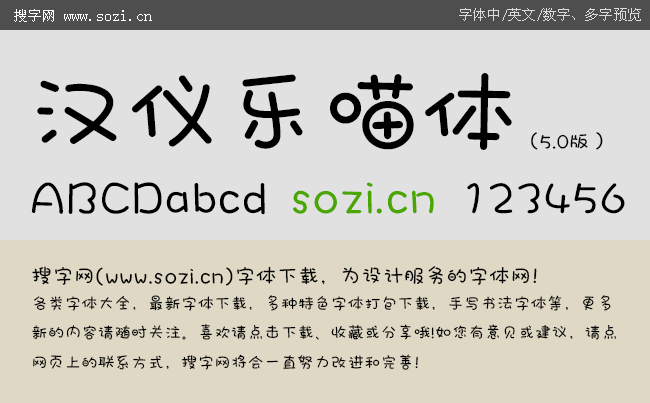
漢儀樂(lè)喵體
搜字網(wǎng)提供一款卡通風(fēng)格的漢儀樂(lè)喵體中文字體下載,漢儀樂(lè)喵體是一款非常靈動(dòng)可愛(ài)的字體,字形秀美圓潤(rùn),用最單純的線條語(yǔ)言表達(dá)最跳躍真實(shí)的韻律,帶有樸實(shí)、童真、活潑、俏皮可愛(ài)、親切之感,可廣泛應(yīng)用于卡通設(shè)計(jì)、正文標(biāo)題、廣告設(shè)計(jì)、平面設(shè)計(jì)、印刷包裝等領(lǐng)域。